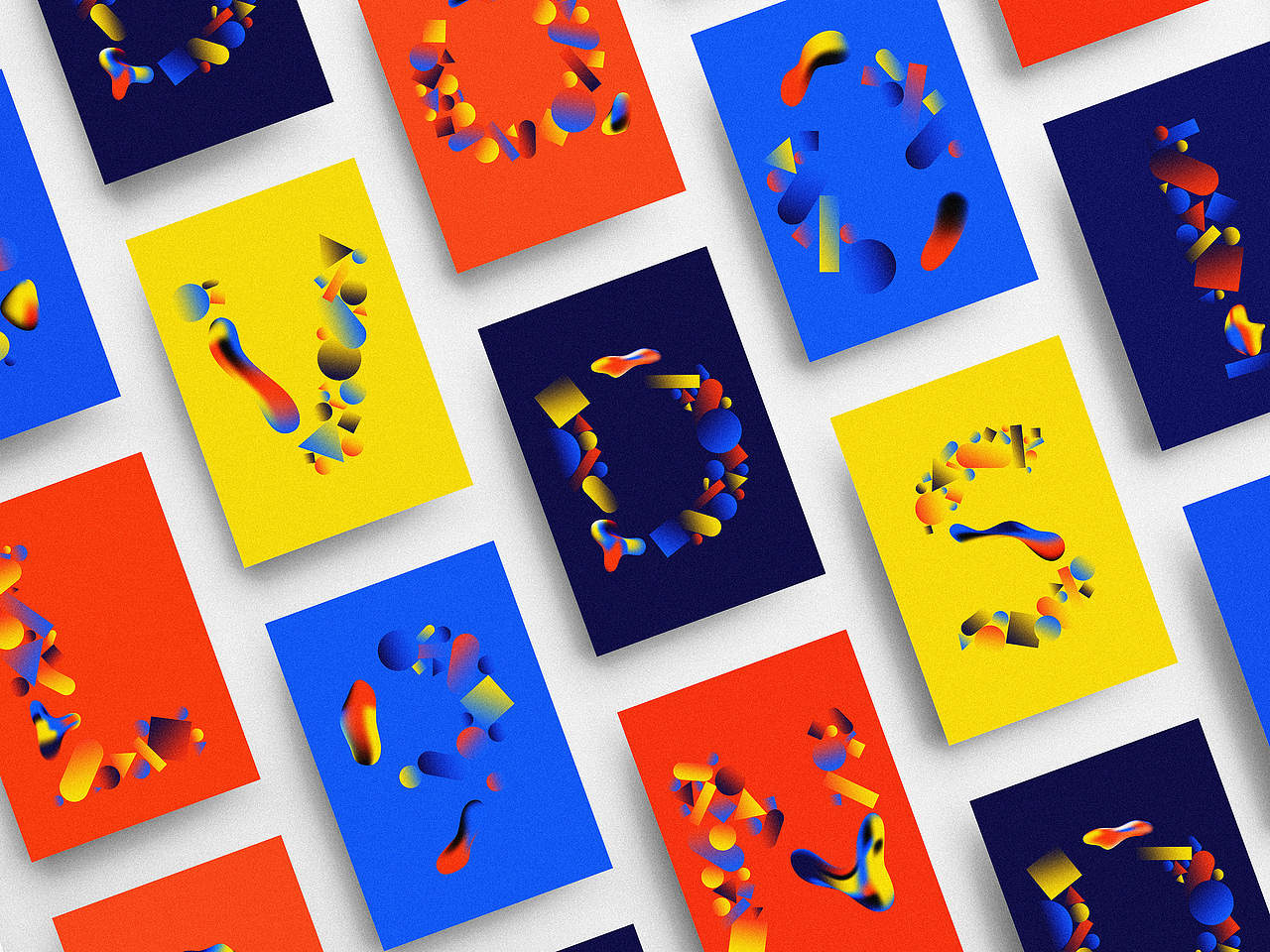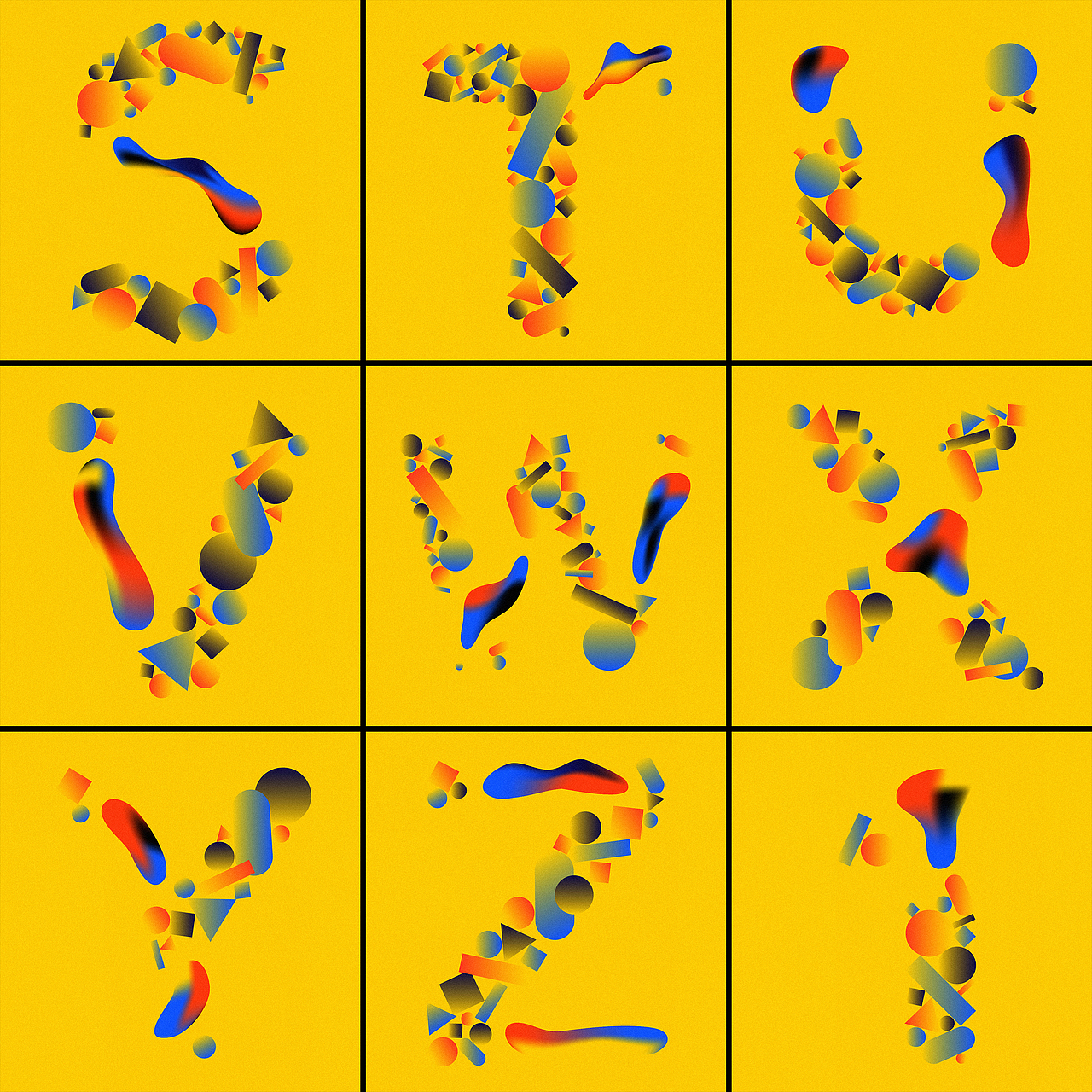
字体设计 | 36 Days of Type
36 Days of Type是一个字母表设计项目,来自世界各地的设计师,插画家和图形艺术家通过对字母和数字的重新设计,带给人们全新的视觉享受。我为项目命名为FLOW,字体主要由规则几何元素色块与不规则形状构成,通过探索颜色,纹理,形状的不同组合,表达出字符的动感。